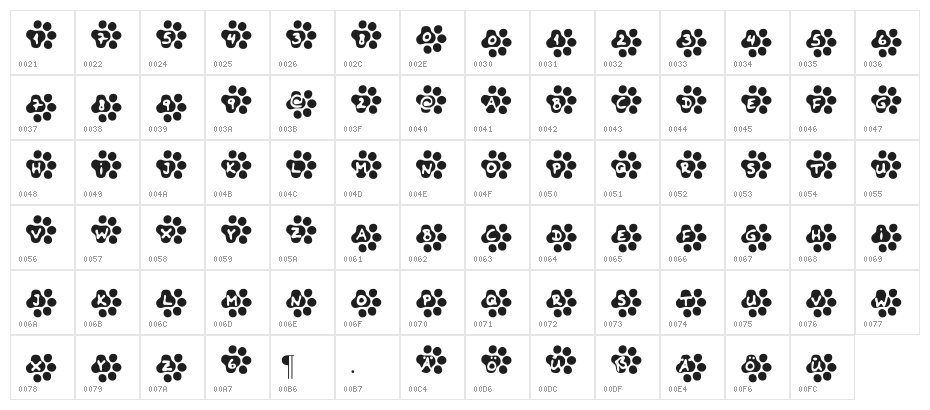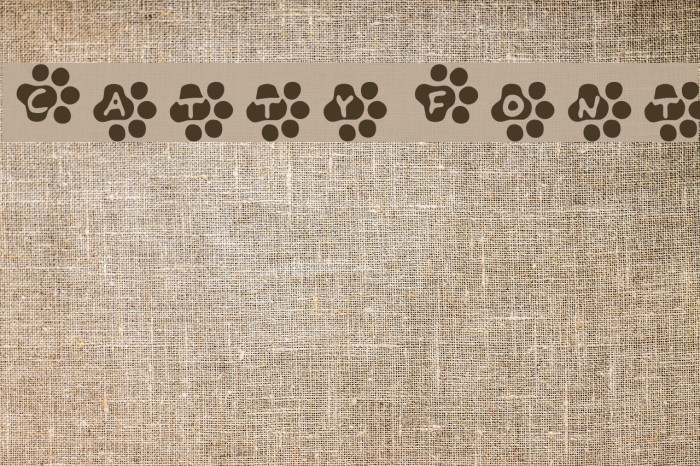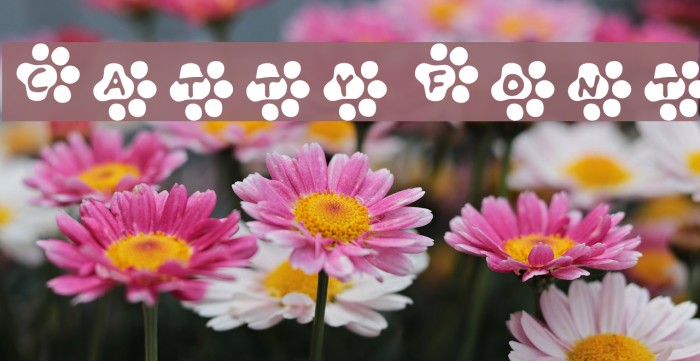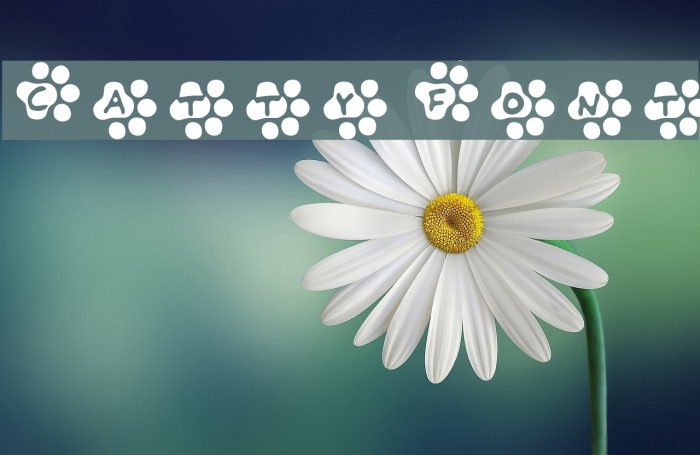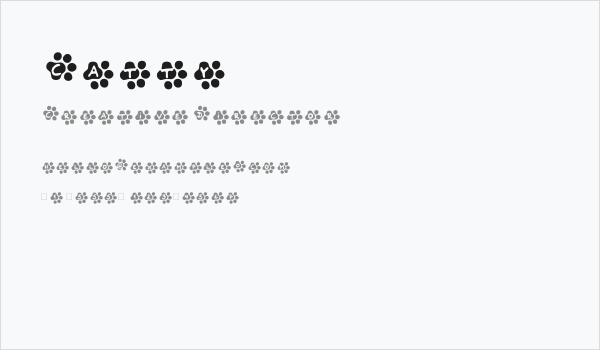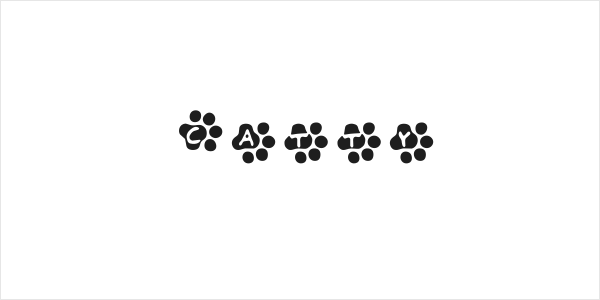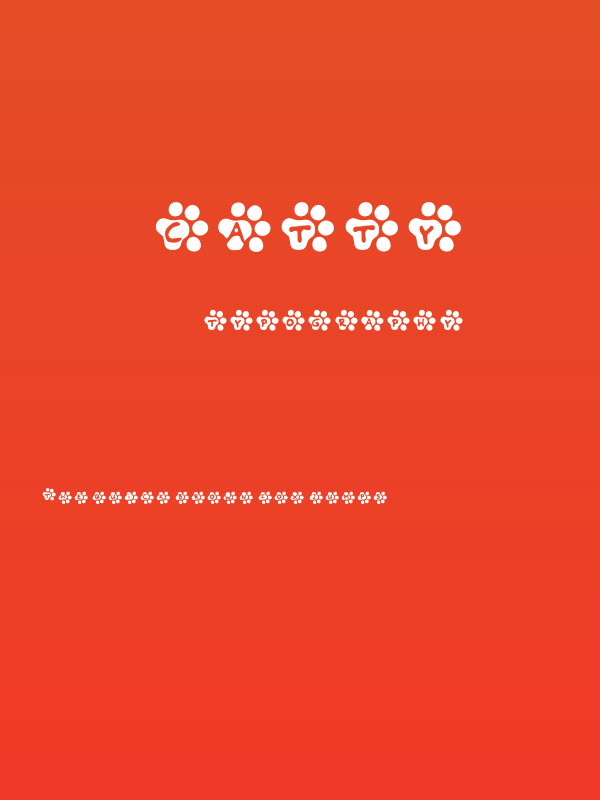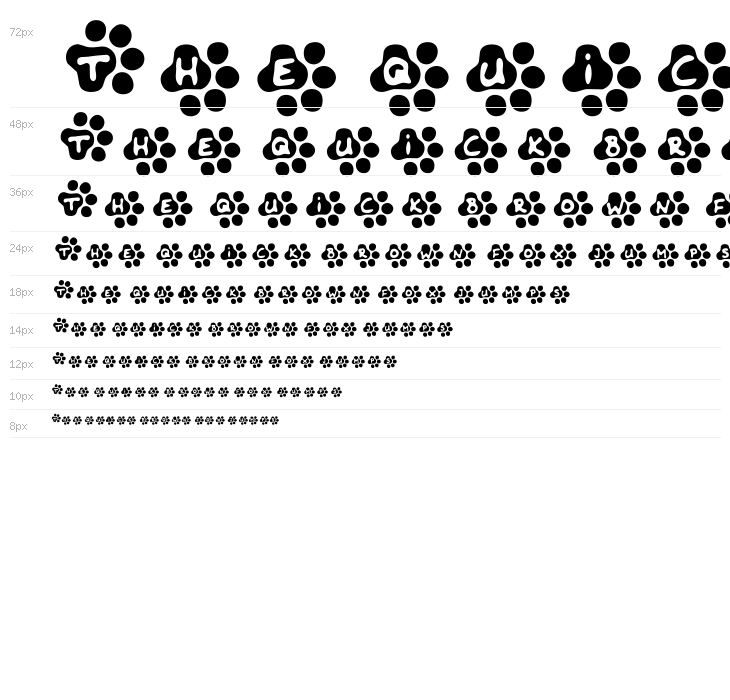
Catty Font
| Gesamtstil | Playful |
| Anwendungsfall | Logos, Posters, Children's materials |
| Vorgeschlagene Projekte | Ideal for children's books, pet-related branding, playful posters, and educational materials. |